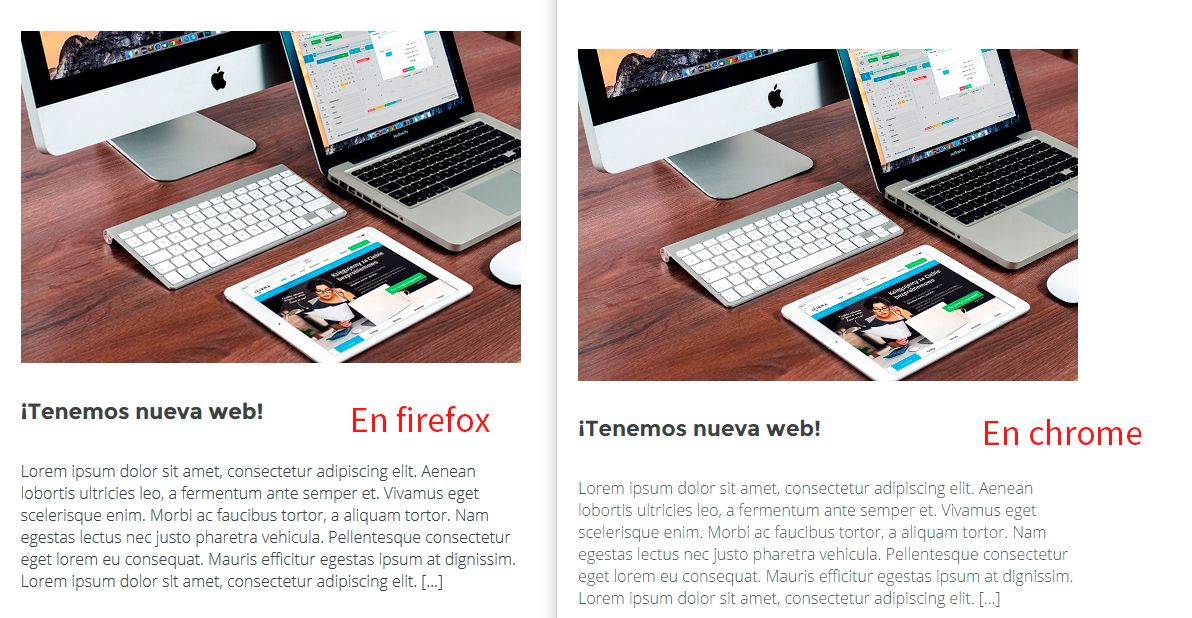
Problemas con fuentes Light (Google Font)
Me está pasando algo curioso al intentar hacer un diseño que tengo pensado...me estoy topando con una diferencia bastante grande en las fuentes cuando aplico el "grosor" Light.
En la imagen veis a la izquierda cómo se ve en Firefox y a la derecha en Chrome. En Firefox se lee muchísimo mejor que en Chrome y no entiendo por qué.
En el código tengo importado la fuente
<link href="https://fonts.googleapis.com/css?family=Montserrat:400,700|Open+Sans:300,400,700" rel="stylesheet" />
Y en mi CSS tengo lo siguiente
html,body{-webkit-text-size-adjust:100%;-webkit-font-smoothing: antialiased;}
¿Por qué se nota tantísima diferencia de una a otra?